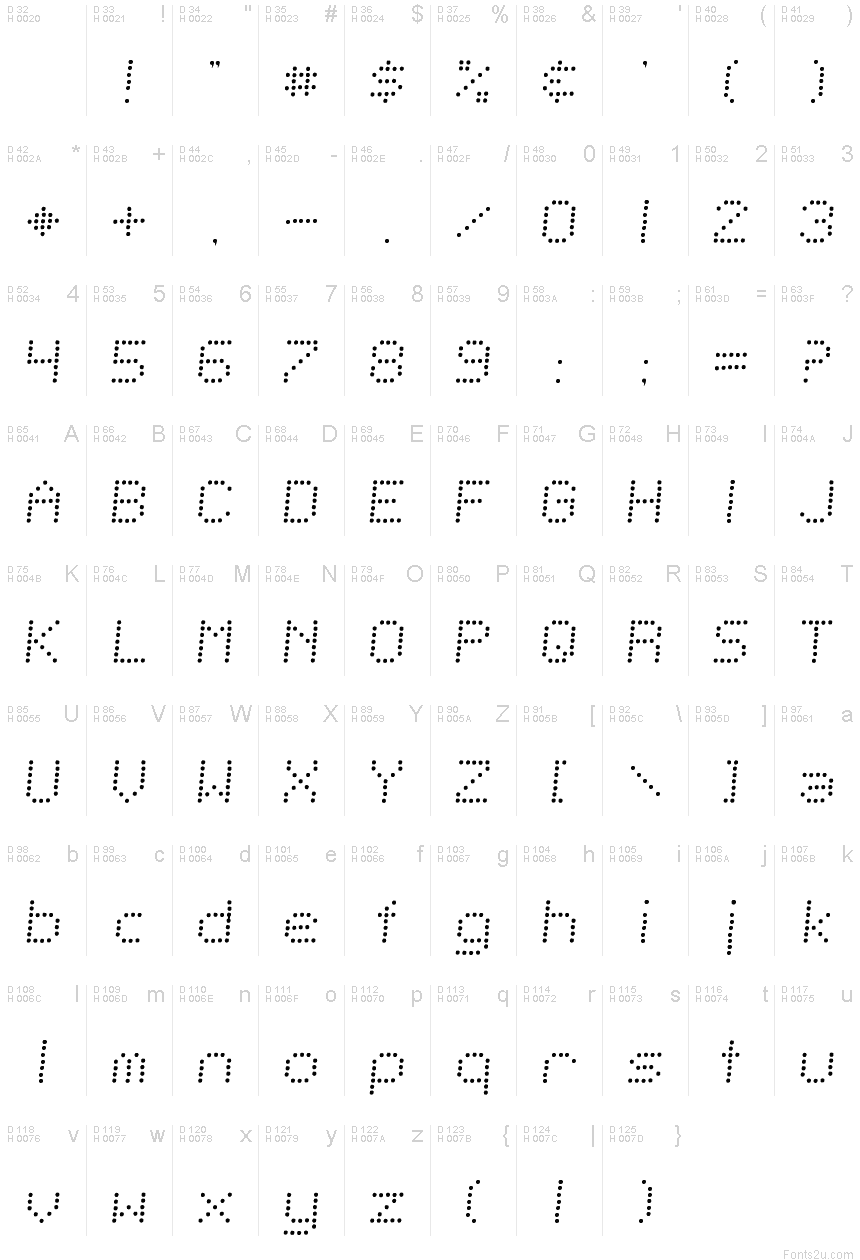
Telegraphic Light Bold Italic
Telegraphic Light Bold Italic, darmowy cyfrowy font ekranowy stworzony przez ShyWedge w 1999 roku, swoją formę opiera na równych rzędach okrągłych kropek, które kojarzą się ze starymi tablicami ogłoszeniowymi lub ekranem teletekstu. Mimo pogrubionego kroju litery sprawiają wrażenie lekkich, a delikatne pochylenie i otwarty, modularny rytm sprawiają, że pikselowa estetyka wydaje się autentyczna i przekonująca.
Font ten naturalnie wpasuje się w plakaty technologiczne, grafikę retro gier, ulotki muzyki elektronicznej, plansze tytułowe czy branding inspirowany interfejsami, gdzie darmowe pismo z takim kropkowanym sygnałem potrafi udźwignąć cały koncept. Wykorzystaj go w krótkich nagłówkach, pomysłach na logotypy, napisach na okładkach czy datownikach, gdy chcesz, aby tekst wyglądał jak przesyłany sygnał, a nie jak wygładzony skład.